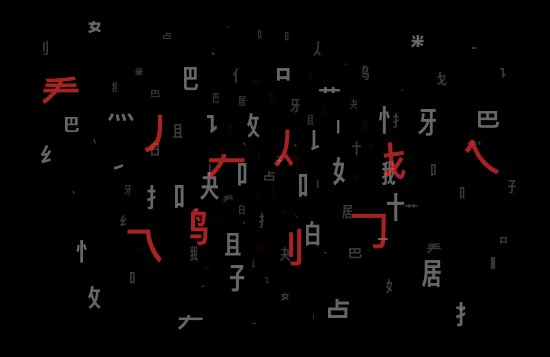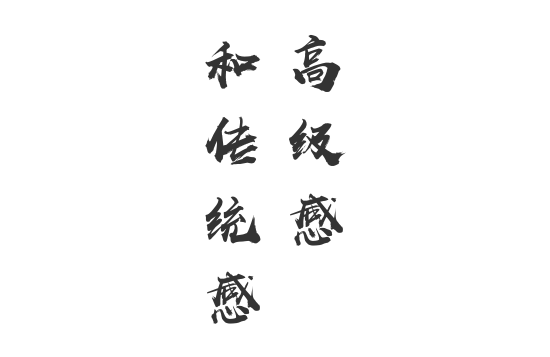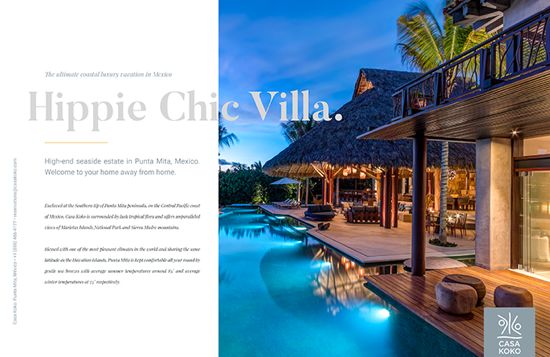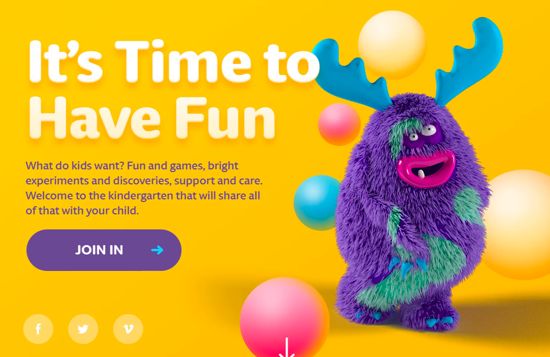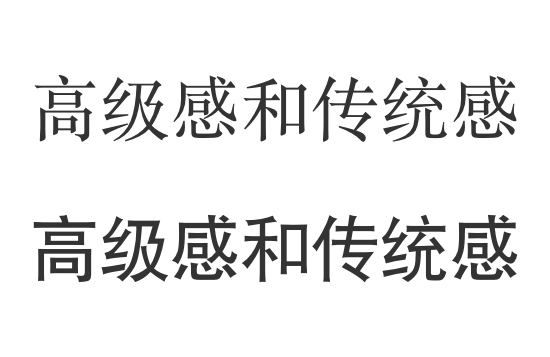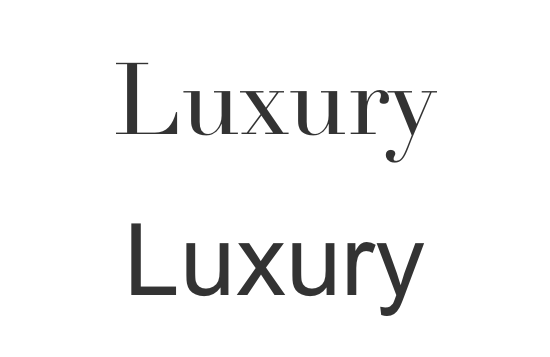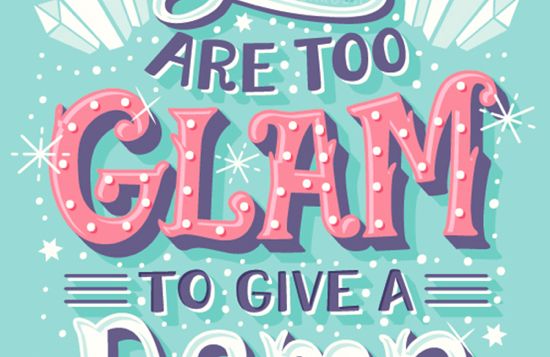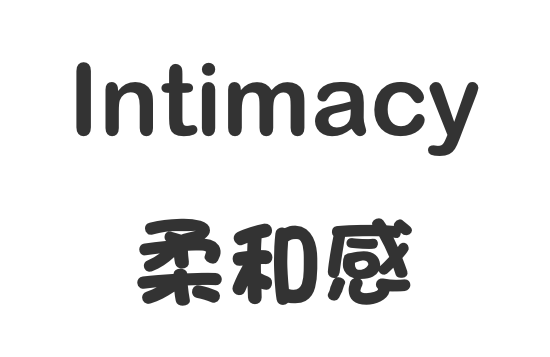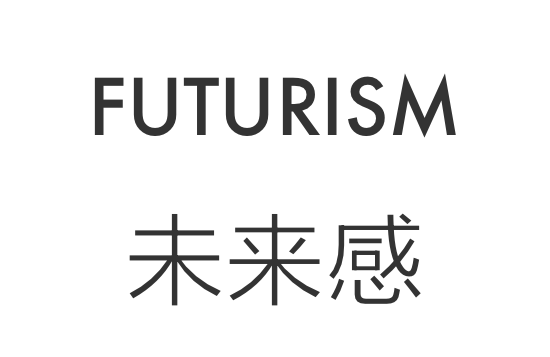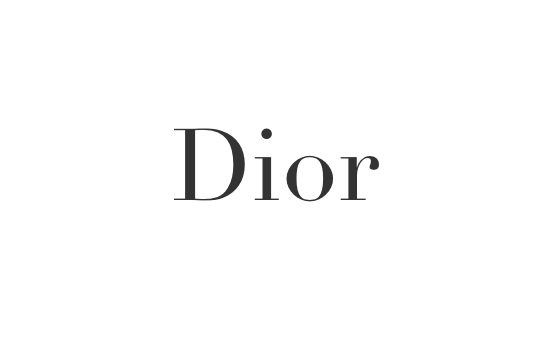
为什么某种文字会给人某种印象,文字与其意像
//前言//
人们在阅读是时候,只专注于文章的“内容”,而文字的形状、线条等视觉信息,却会在同一时间映入眼帘。这些信息会以模糊的“意象”留存在读者的脑海中。
不同于阅读文字的内容,“意象”会让人“直觉”且“无意识”的接收并且印刻在心中,构筑成形。
诚品书店
中国台湾艺术大学毕业展
COL设计展
艺术拓展未来
THERAPY
如果你只是文字的阅读者,可不必对这样的意象深入细想;但如果你是负责文字的设计人员,从创作者的角度,你就必须思考积极创造“意象”并加以控制的方法。
本文将会针对文字与设计给人的意象做一番具体的介绍,也就是说,为什么某种文字会给人某种印象。正是这个“为什么”,是我们本文的重要部分。
//高级感和传统感//
我们通常理解的高级感或传统感,一般就是文字的优美曲线与其周边的空间所营造出来的氛围。
一般来说,在我们使用西方语系文字时,衬线体会比无衬线体来的有格调;
而东方语系文字中,宋体感觉比黑体要来的高雅。
最主要的原因是衬线体和宋体相对无衬线体和黑体来说,厉害更为悠久,并长期为人们所使用。
在印刷中,衬线体本身就给人一种“传统”和“高格调”的印象。如果更进一步,采用历史久远、类似手写体的文字设计,则更能体现出强烈的传统感和高级感。
那为什么这样的字体会显得更有质感呢?
这些传统的字体设计都有一个共同点,就是字体中大多有曲线。有些字体可能只是很少的曲线,但借由这些曲线搭配而组成的字体,却能营造出优美而又华丽的感觉。
此外,想要呈现出高级感,别忘了在文字周边的“留白”以及文字的“颜色”。让文字周围有舒展的空间,字号不显得过大,这点非常重要。
字的颜色尽可能选用近乎无彩色、不会给人艳俗感的颜色为准。
//亲近感和柔和感//
我们在看到形状尖锐细长的东西,会感到紧张。相反,没有边角的圆滑形状,则会带来“安全感”“容易亲近”的印象。
文字也带给我们同样的心理作用。线条纤细、前端尖锐的直线形设计文字,给人危险、难以靠近的印象;
至于线条粗大、前端浑圆的文字设计,则给人容易亲近、柔和或者可爱的印象。更进一步来说,采用类似手写的随性字体,更能加深这种印象。
在颜色上,采用与背景色差异小的暖色系,尽量避免黑色或者藏青色等强对比色彩,保证文字温柔的印象。
边角浑圆的字体让人觉得很容易亲近,但同时也带来了“孩子气”“‘轻浮”的印象;同时,这类有“特征”的字体,不适合应用于长篇文章,容易造成疲倦。
//未来性和先进性//
我们在设计具有“先进”“精致”“未来”意象的作品时,也可通过文字来达到这样的意象。
首先,我们排除来带有装饰的文字。文字构成要素越简单,抽象感则越强烈,更容易呈现出一种现代感。
无衬线体比衬线体更简单,黑体比宋体更简单,所以在无衬线体和黑体中去选择具有未来感的字体更容易。
其次,想要进一步带来科技感,在文字要素简单的基础上,呈现出“图形化”。
例如,只用直线来呈现文字,或者只用直线和圆相互连接来构成文字。这样的字体更多出现在西方语系文字中,中文这种复杂的文字很少有这个类型的。
文字越是图形化,就越难以把他当作“文字”来阅读。尽管在“logo”和图像广告中经常出现,但是在长篇的文章中显得难以阅读,非常不实用。
在颜色上,想要营造出充满先进感、未来感的意象,适合使用黑灰色或者深颜色。在重点的部位点赞红色、蓝色等,进一步加深来科技感。
//怀旧和复古//
很多文字的出现都是符合当时的时代风貌,所以以前的部分文字设计,就会具有很强烈的复古感。
我们在设计怀旧作品的时候,了解那个时代的文化特征,巧妙掌握流行的走向、转变及其设计的特色,能够更好的帮助我们作出充满怀旧感的设计。
在中文字体中,上世纪50年代左右的设计作品里,手写字体的设计带给人温暖和柔和的感觉。
那个时代还是无法完全使用印刷技术,因此采用手写字体来描绘设计。正是因为如此,线条的粗细带有随意性,笔画也不是非常的统一,正是这一特点,更能体现当时的时代文化。
在西方语系文字中,类似“罗马体”“哥特体”等代表性的复古文字,体现出来当时古老的文明;
后来随着时代的发展,字体也由严肃转变为更多的装饰;
再之后,便是“新文字艺术”的风潮影响下,文字设计开始产生“现代感”。
//传统文化与书法文字//
若要问哪个字体设计让你感受到了传统文化,非竖排的毛笔字莫属。
在中国书法中,“篆书”、“隶书”、“楷书”、“行书”、“草书”称为书法五体。
除此之外,还有在logo、或者广告标语设计中,更自由、更具有现代感的毛笔字设计,也有委托书法家亲手书写的。
书法字体最重要的便是毛笔的运笔走势和排列方式要一致。毛笔字多采用竖排,若是以横排来展示,会觉得有点古怪。
在颜色上,传统毛笔字不适合鲜艳明亮的颜色,减少整个版面的色彩,多采用古朴的配色,更能体现出中国字体的传统感觉。
//严谨感与信赖感//
原本文字不具有设计性,只是传递“信息”的载体。而传递的信息难免也会有误,或者是胡诌骗人的内容。
说谎的人会显得神色惊慌,或是刻意装模作样;相反,严谨、值得信赖的人,则会显得稳重、朴实,不会标新立异。
文字设计也一样。充满装饰性、给人华丽印象的设计,显得魅力十足,也更容易引起人们的兴趣和关注;
但是在“信赖感”这方面,常见且没什么特别独特性的文字则更胜一筹。例如,历史悠久的宋体比黑体更具有信赖感。
在文字排版上,版面宽松、阅读的设计,比紧凑的版面设计更让人信赖。
//精致的印象//
相信我们或多或少都有收到要求精致设计的需求,而想要营造出精致的印象,文字的配置方式比采用任何字体更为重要。
在文字选择上,比起宋体和衬线体之类历史悠久的文字设计,新颖的黑体和无衬线体更能给人现代感、利落、清爽的印象。
而纤细线条的文字比起粗线条的文字给人更强烈的精致感。
最后要达到“精致”印象的设计,比起文字本身的形状,对文字的布局环境进行精细的调整更为重要。
首先,文字的周边应该有足够的空间,对文字做精简的浓缩,大胆的让文字的周围有大块的留白。在缩小字体的同时,尽量减少字数。
同时,尽量减少版面重的色彩数量。多采用无彩色,或者近乎灰阶的灰色调,便能呈现精致风格。
//力道与冲击力//
想强调存在感、想表明主张或是想要让文字内容呈现出冲击力,可将直线形的文字放大,借此呈现出力道、冲击力。
比起宋体和粗线条这种纵横线条宽度不一的设计,黑体和无衬线体这种线条宽度一致的文字更具有稳定感,适合表现力感。而构成线条越粗、越能给人强劲的感觉。
在版面上,松散的字间距会削弱文字的力量感,让文字稍微紧缩,更能表现出力道。
若版面上有过多的文字,采用粗黑的字体设计,则会让画面显得沉闷,削弱了文字的对比。我们只有在该使用粗字体的时候使用,和其它的字体产生对比,才更能展现粗字体的力量感。
在颜色上,文字要挑选与背景色有明显差异的颜色。在所有颜色中,黑色最能表现出强劲意象,不管和什么颜色的背景搭配,强劲感都不会削弱。
//纤细与魅力//
在以女性为对象的设计作品中,经常要求呈现出纤细、优美、华丽的意象。在文字选择上,可选择线条纤细,整体为曲线形式的字体。曲线比起直线更为柔和、更容易亲近。
在东方语系文字中,宋体比黑体更适合女性设计,在西方语系文字中,衬线体比无衬线体则更胜一筹。
想要进一步强调“魅力”,采用草书或者楷书这类的毛笔字体也是不错的选择。
进一步细分来看,年轻女性的设计,整体采用曲线组成,端角圆滑、给人可爱印象的文字;
以女性为对象的商业类设计,则可采用黑体或无衬线体来代替;
想要传达优雅的高级感,则避免使用新型设计的文字,采用传统的宋体或衬线体跟更适合;
如果想要表现休闲的风格,就该选择强调装饰性的文字设计。
//小结//
随着字体不同,文字可以传达出不同的氛围,加以色彩的配合,能传达出更明确的意象。
但文字设计不是万能的,有时候文字没法完美的呈现出想要的意境,这个时候,整体上调整版面布局和色彩搭配,可以最有效的帮助画面去表现原本想要展现的意境。